Tipográfiaa design központi eleme, amelyet gyakran figyelmen kívül hagynak. A megfelelő betűtípus választása jelentős hatással lehet a designod és olvashatóságának észlelésére. Ebben a cikkben megtanulod, hogyan dolgozz hatékonyan a betűtípusokkal és a tipográfiával AdobeXDprogramban. Megtudod, hogyan találhatsz, telepíthetsz és használhatsz optimálisan betűtípusokat a projektedben.
- Betűtípusokat szerezhetsz be a Google Fonts és Adobe Fonts szolgáltatásokról.
- Két alapvető szöveg eszköz található az Adobe XD-ben: Pontszöveg és Szövegdoboz.
- A betűméret és a sortávolság kulcsfontosságú az olvashatóság szempontjából.
- Definiált karakterformátumokkal időt és energiát takaríthatsz meg a szövegformázás során.
2. Szövegdobozok és pontszöveg létrehozása
Az Adobe XD segítségével most már kezdhetsz szöveget létrehozni. Használd a T billentyűparancsot a szöveg eszköz aktiválásához. Készíthetsz egy szövegdobozt úgy, hogy rákattintasz, vagy szövegdobozt húzhatsz ki az elhelyezéshez.
Tartsd észben a különbséget: Ha egy pontszövegdobozba kattintasz, a szöveget egyetlen sorba írod be. Szövegdoboznál a szöveg automatikusan a következő sorba törik, ahogy eléri a rendelkezésre álló szélességet.
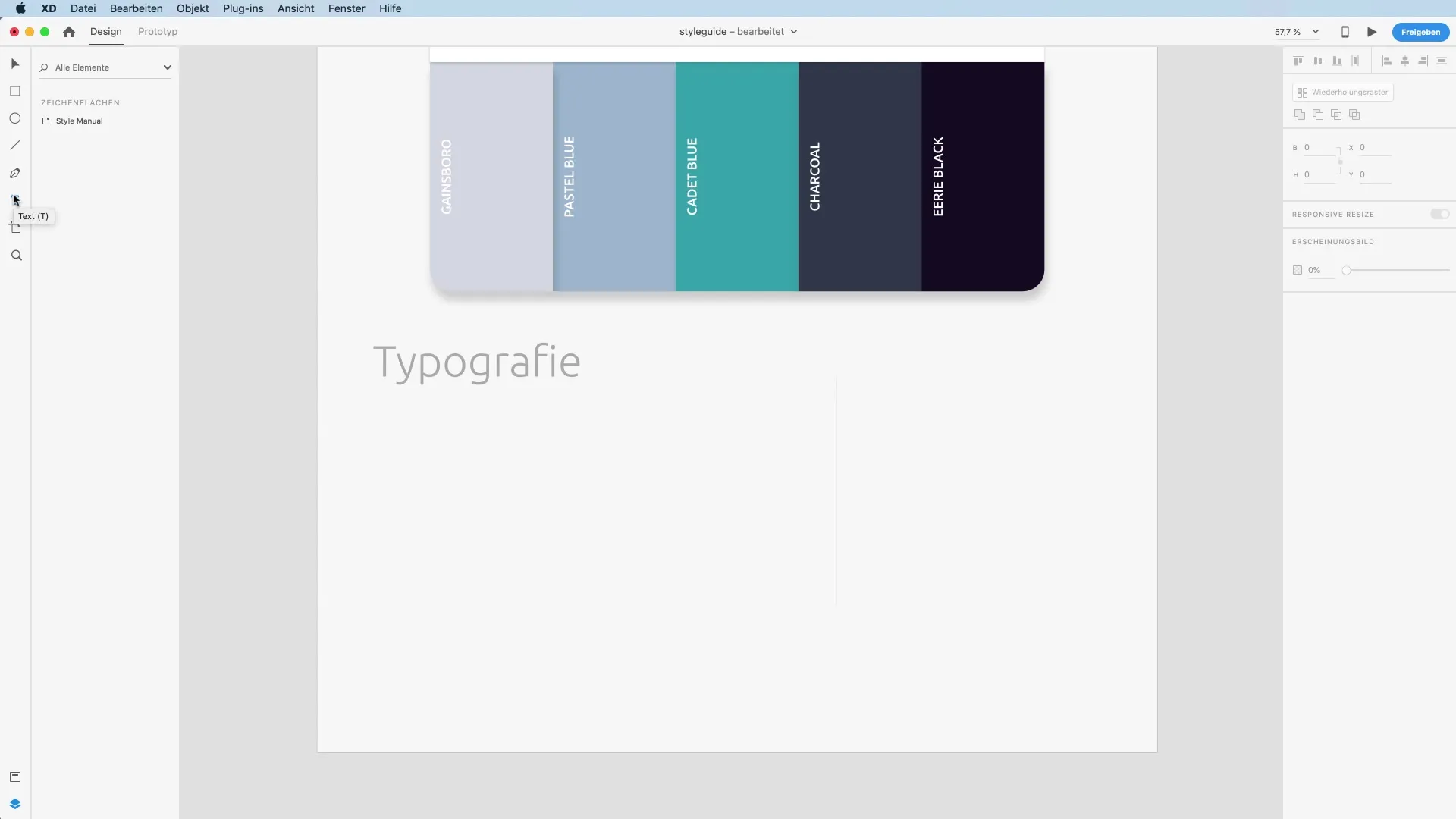
3. Szövegstílus és -méret beállítása
Ha már írtál be szöveget, a betűméretet és a betűstílust az Adobe XD jobb paneljén állíthatod be. Állítsd a betűméretet körülbelül 30 pixelre, és válaszd ki a „Közepes” betűstílust.
A szövegdoboz méretének növeléséhez vagy csökkentéséhez egyszerűen húzd meg az egyik fogantyút. Fontos, hogy a szövegdoboz mindig elegendő helyet biztosítson a beírt szöveg megjelenítéséhez.
4. Távok és sormagasság beállítása
A tipográfiai design megérzést igényel, különösen a távokkal kapcsolatban. A jobb panelen beállíthatod a karaktertávolságot és a sormagasságot. Kísérletezz ezekkel az értékekkel, hogy biztosítsd, hogy a szöveg jól olvasható legyen és esztétikus kinézetű.
Figyelj arra, hogy vékony betűstílusok esetén nagyobb betűméret szükséges a megfelelő olvashatóság érdekében. Lehet, hogy egy kicsit vastagabb betűstílust kell választanod, ha kisebb betűméreteket használsz.
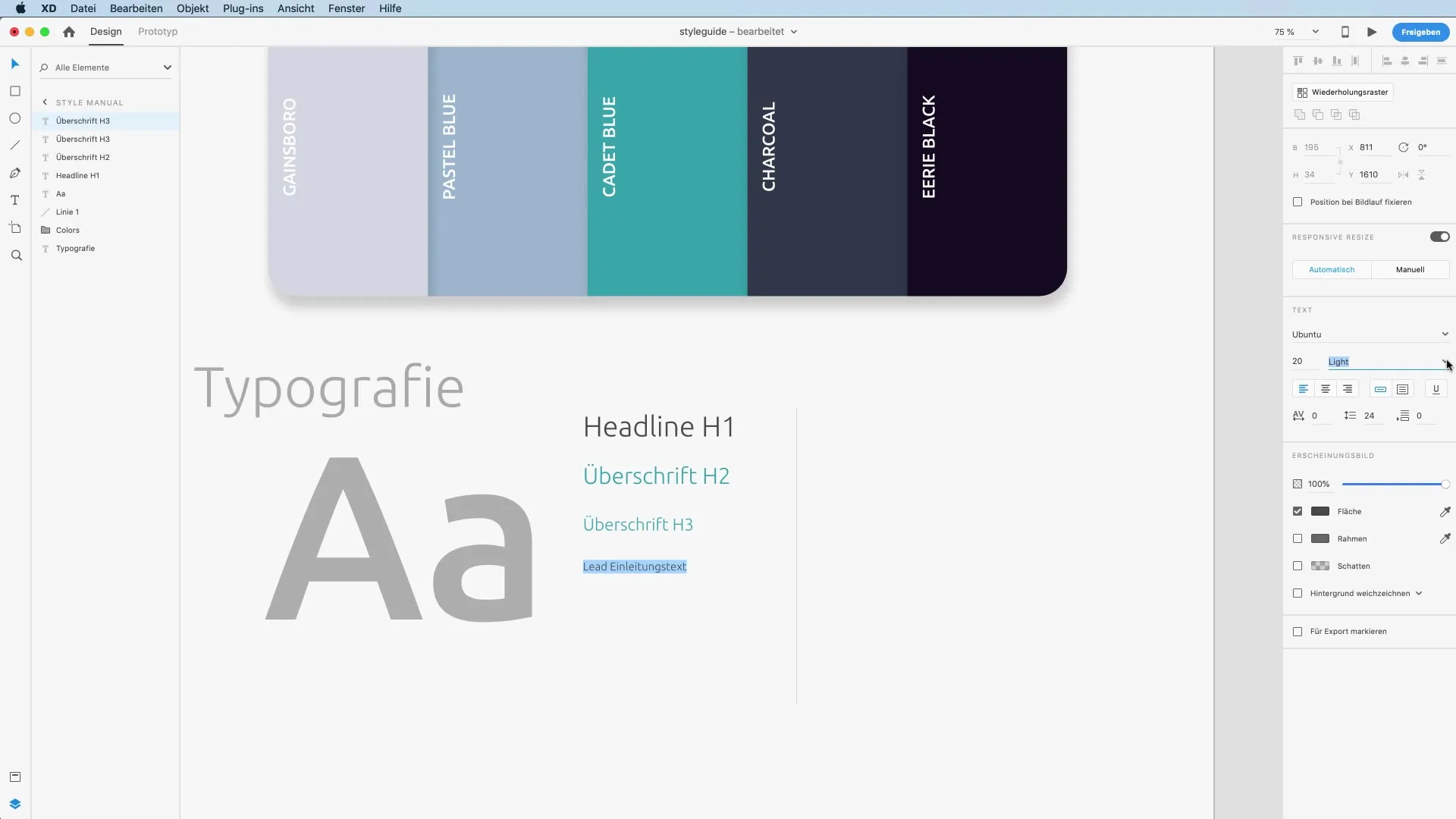
5. Több betűstílus definiálása
Különböző betűstílusokat hozhatsz létre a címek, alcímek és szöveg számára. Például hozz létre különböző szövegdobozokat 50px, 40px, 30px és 20px méretben, és ne felejtsd el, hogy megfelelő betűstílust válassz.
A betűtípusokat ezután a jobb oldalon állítsd be egymás mellé. Így gyors áttekintést nyerhetsz a meghatározott stílusaidról.
6. Karakterformátumok mentése
Az Adobe XD egyik különösen praktikus funkciója a karakterformátumok mentésének lehetősége. Ha már létrehoztál egy címet, elmentheted ezt a formázást, és később egyszerűen alkalmazhatod más szövegre. Nevezd el a formázást úgy, hogy leírja, mi az, például „Cím H1” vagy „Bekezdés”, hogy átlátható maradjon.
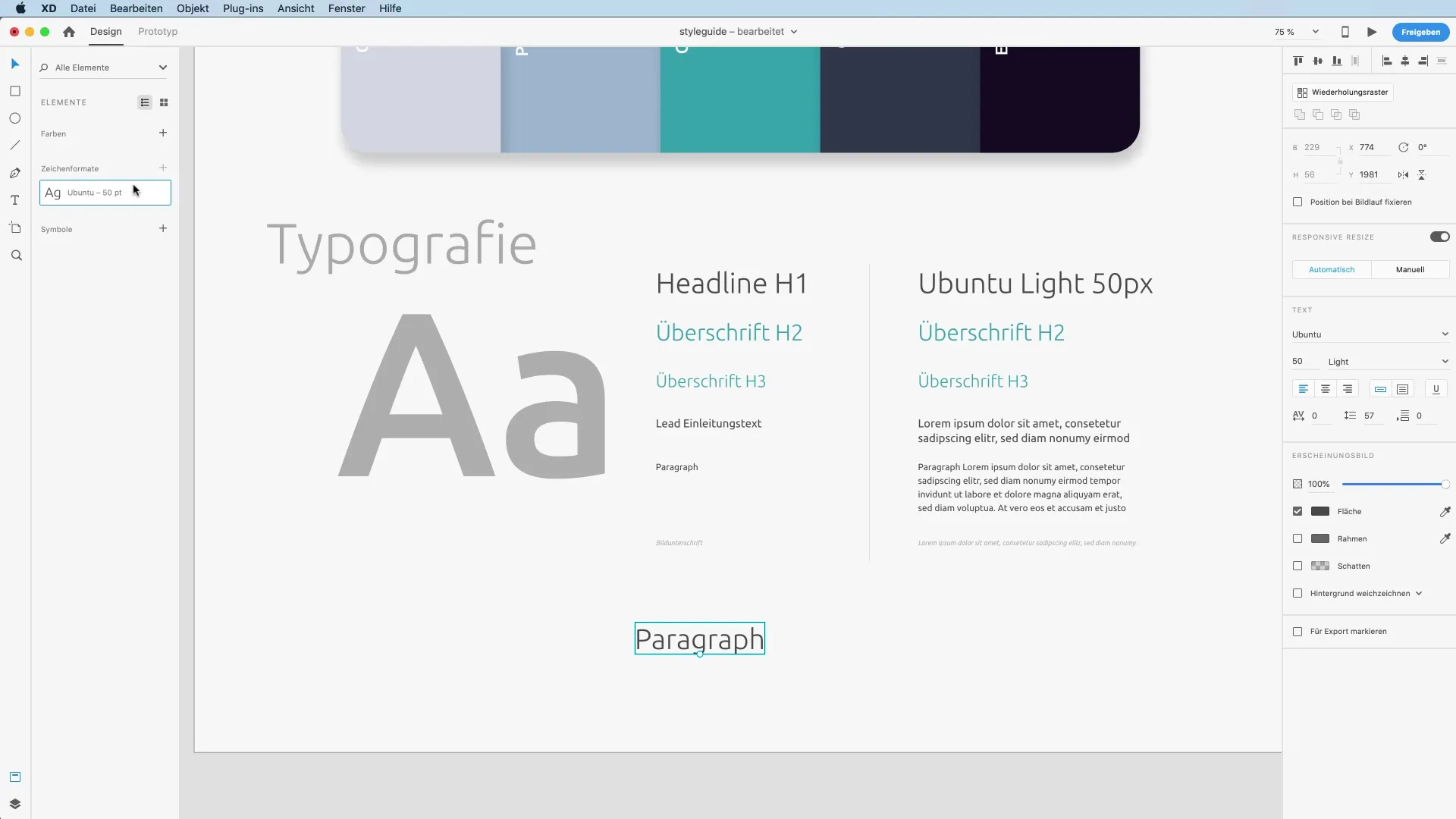
7. Szövegformázások alkalmazása meglévő szövegekre
A formázások gyors alkalmazásához az előzőleg definiált stílust alkalmazhatod új szövegekre a karakterformátum menü segítségével. Ez jelentősen felgyorsítja a munkafolyamatodat, hiszen most már nem kell minden módosítást manuálisan elvégezned.
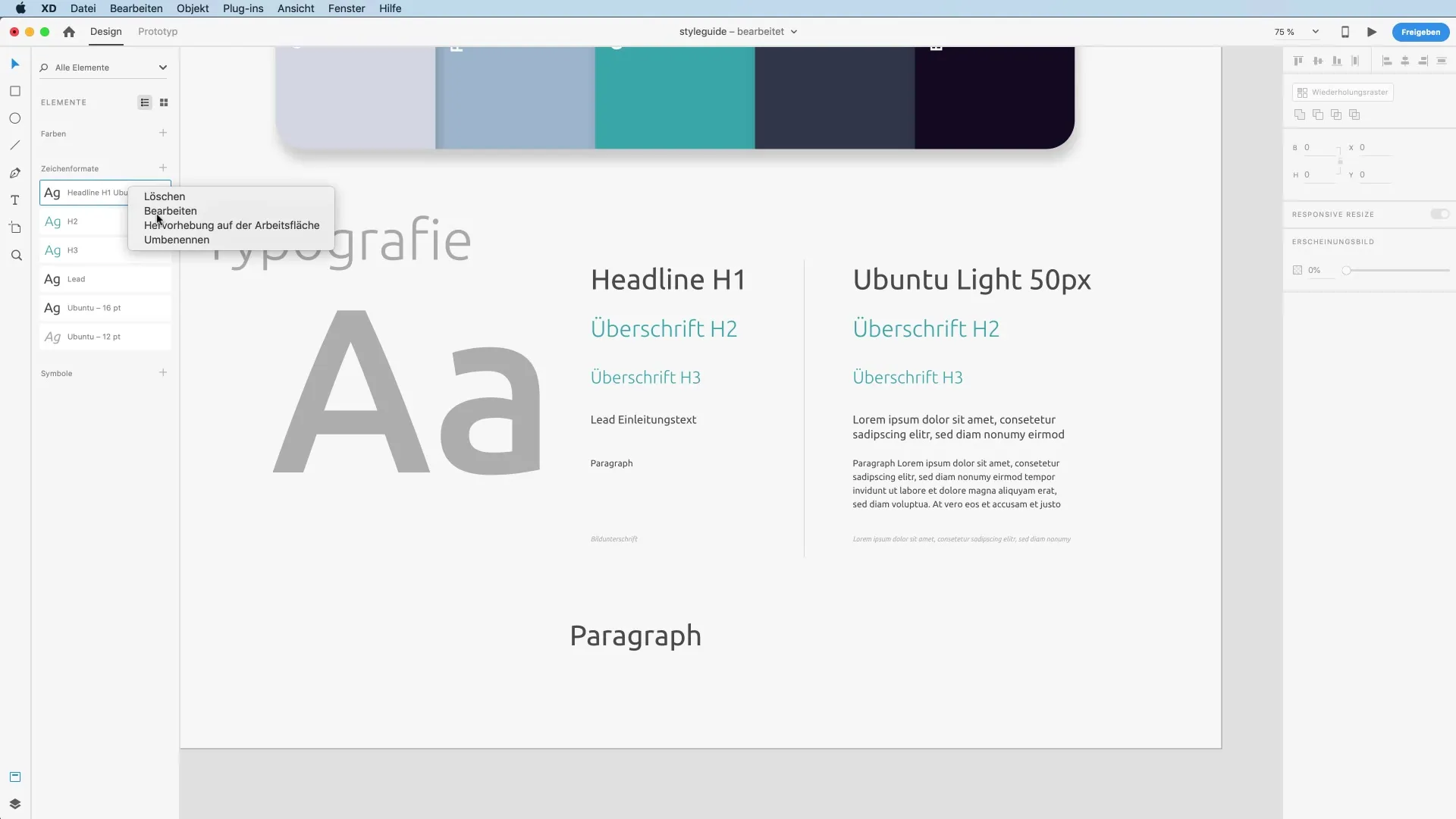
8. Szövegek szerkesztése a dokumentumban
Ha változtatásokat szeretnél eszközölni egy stílusnál, például a betűstílus vagy a méret módosítását, ezt a karakterformátumban teheted meg, és a módosítások azonnal alkalmazásra kerülnek az összes olyan szövegre a dokumentumban, amely ezt a formát használja.
Összefoglalás – Optimalizáld a szöveget és a tipográfiát az Adobe XD-ben
Ebben a útmutatóbanmegtanultad, mennyire fontos a megfelelő betűtípusok kiválasztása. Megtudtad, hogyan találhatók meg, telepíthetők és alkalmazhatók hatékonyan az Adobe XD-ben. Karakterformátumokat menthetsz, hogy konzisztens maradj, és optimalizáld a munkafolyamatodat. Ne feledd, hogy a tipográfiának nemcsak szépnek, hanem funkcionálisnak is kell lennie az olvashatóság garantálása érdekében.
GYIK
Hogyan találhatok jó betűtípusokat a projektemhez?Nézd meg az olyan platformokat, mint a Google Fonts és az Adobe Fonts.
Hogyan telepítsek betűtípusokat a rendszeremre?Jóváhagyott instrukciók szerint töltsd le a betűtípusokat és telepítsd őket a platformodnak megfelelően.
Mi a különbség a pontszöveg és a szövegdoboz között?A pontszöveg egy egyszerű beviteli sor, míg a szövegdobozban a szöveg törik, amikor a szélesség eléri a határt.
Hogyan állíthatom be a karaktertávolságot az Adobe XD-ben?Ehhez egyszerűen módosítanod kell a megfelelő beállítást a jobb panelen.
Menthetek betűstílusokat az Adobe XD-ben?Igen, menthetsz karakterformátumokat, és ezeket később más szövegdobozokra alkalmazhatod.